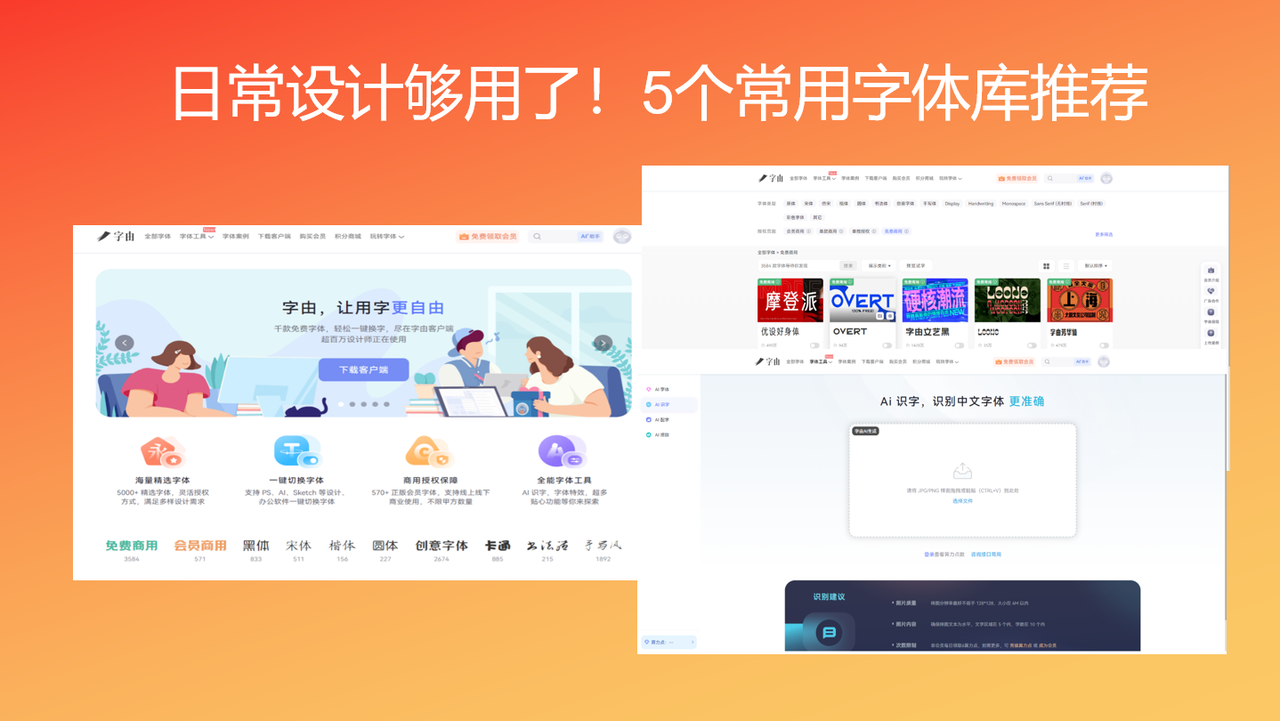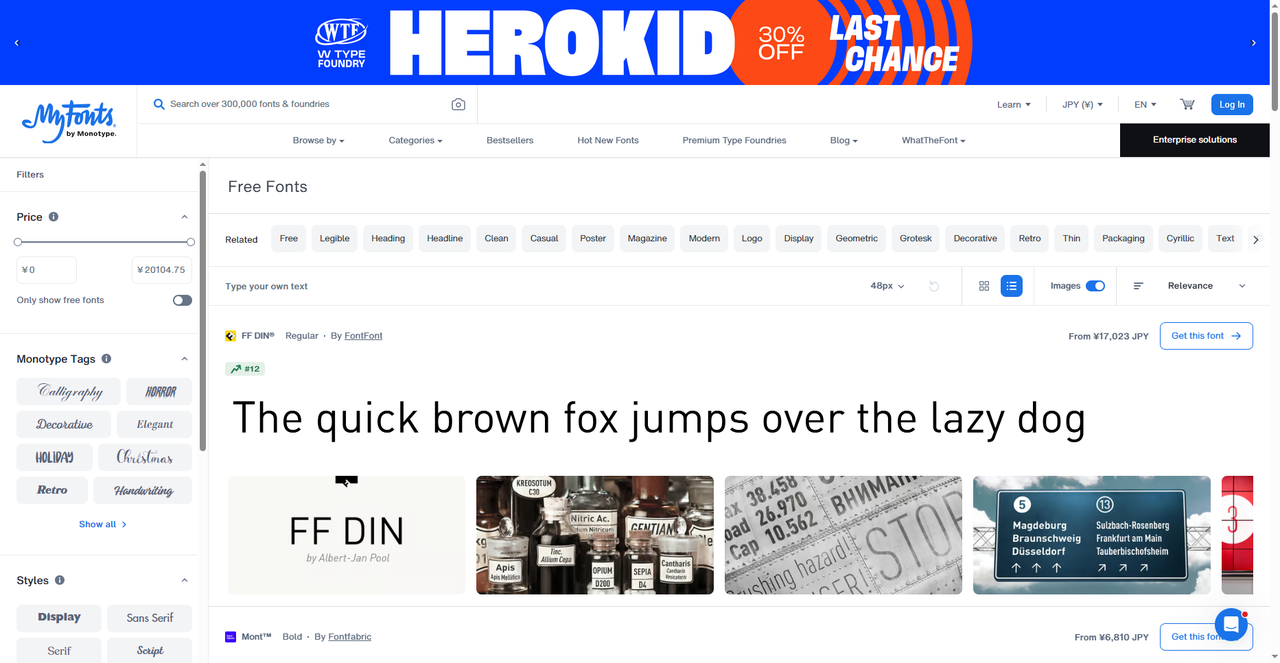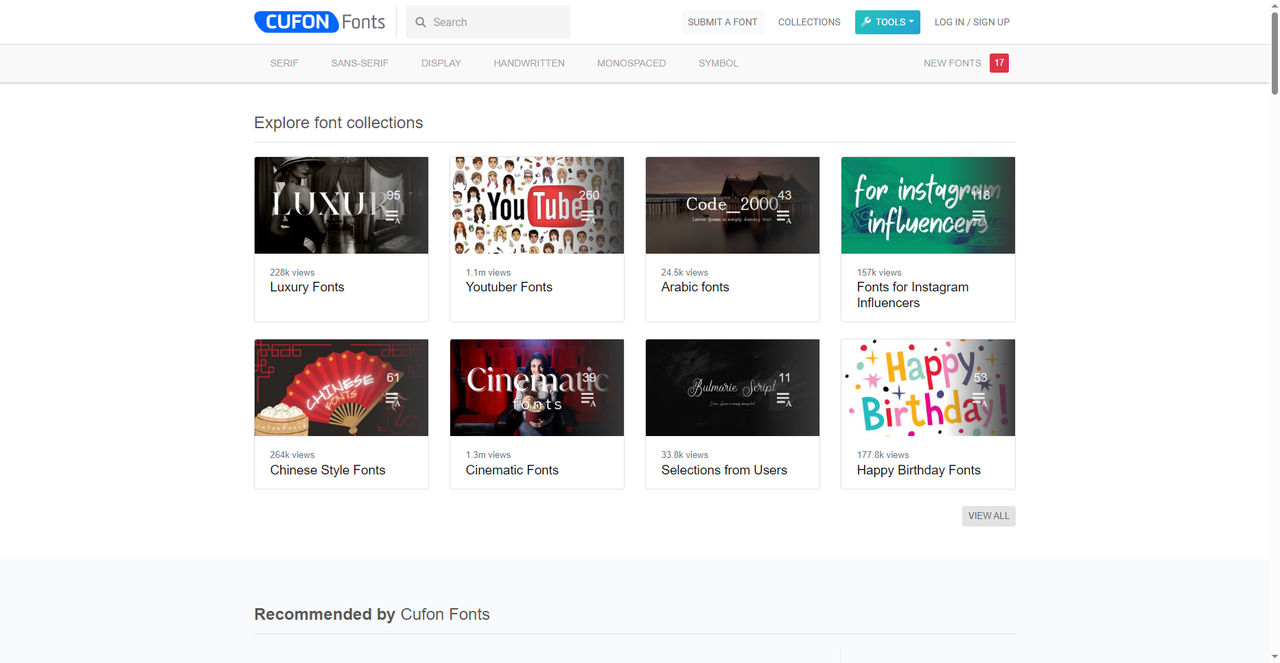
日常设计够用了!5个常用字体库推荐
如果你是刚做设计的新人,肯定免不了会以为好字体是要找的,一开始会到处问别人用什么字体,或者是看一些字体推荐,收藏了很多文章,结果真的要开始做设计项目的时候还是不知道怎么下手。但其实好的字体是要靠积累的,而不是现用现找,这样只会使自己设计思路更乱。那我今天就会给大家分享5 个我用着十分顺手的常用字体库,没有灵感的时候就可以随时点开翻看,遇到好用的就收藏积累起来,这几个都是我打开过无数次、真正能用到日常设计里的字体库网站。
第一个要推荐的常用字体库是字由。字由自从创立以来便一直致力于解决设计师群体的用字困难问题。2017年,字由客户端正式发布,被粉丝们热情地称为“字体应用管理神器”,并且目前字由还开通了客户端,要比网页面的功能更加全面,使用起来会更加便捷。
字由之所以能够成为我的常用字体库的最主要原因是它有着个人云字库管理功能,之前我都是把自己的字体包存在U盘里,但是一旦丢失将是不可挽回的损失。字由则替我完美地解决了这个难题,它支持上传本地字体到云端,只要账号还在,换设备登录依旧可以激活使用,电脑坏了、U盘丢了再也不是令我头疼的事情,只要账号还在,字体就一定在。
其次,字由身为我日常最常用到的字体库还有一个重要原因就是它目前有超过 3000 款可商用的免费字体,完全不用担心版权问题。如果是在网上找的资源,则要面临版权问题和使用限制问题,在字由的话会直接给你按分类归纳好哪些字体是个人使用的,哪些字体又是可以商用/免费商用的,十分便捷!
最主要是的,我们平时在做设计的时候基本上都会用到 PS、 AI、Figma、Sketch、CDR 等软件,之前要是想换字体的话基本上需要重启安装,但是有了字由以后你可以实现一键切换字体。在软件里选中文字图层,回到字由客户端点击想要的字体,文字实时切换,不需要下载、安装、重启。
并且字由还有配套的 AI 智能工具,完全无须担心设计上遇到的相关难题,不论是字体搜索还是字体特效设计,字由都可以帮你搞定。
2、HEROKID
HEROKID 是一个精品字体销售平台,从配图我们可以看到正在展示 FF DIN 这款经典字体。FF DIN 由 Albert-Jan Pool 设计,是工业设计感和现代主义风格的代表字体,广泛应用于品牌、导视系统等领域。在网站的左侧有详细的筛选器,可以按价格、风格(如 Clean、Casual、Geometric、Grotesk、Retro 等)、用途(Heading、Poster、Magazine、Logo、Packaging)来筛选字体。如果你在寻找高品质的商业字体,这里是个不错的起点。虽然大部分需要付费,但字体质量很高,适合对品牌调性有要求的项目。这算是我常用的字体库推荐,毕竟设计并不能全部要依靠免费内容,有时候为优质资源付费也是必要的事情。
3、Cufon Fonts
Cufon Fonts 是一个运营多年的老牌字体网站,分类清晰,首页顶部有 Serif、Sans-Serif、Display、Handwritten、Monospaced、Symbol 等常用分类。这个我常用的字体库主要特色是它的字体专题合集功能,从图中不难看出它在主页就已经为我们整理好了各种字体合集:
- Luxury Fonts(奢华风格字体)
- outuber Fonts(适合视频创作者的字体)
- Arabic Fonts(阿拉伯语字体)
- Fonts for Instagram(适合社交媒体的字体)
- Chinese Style Fonts(中国风字体)
- Cinematic Fonts(电影感字体)
- Happy Birthday Fonts(生日主题字体)
不仅仅是这些,还有更多内容你可以去探索和尝试,并且每个合集保底都有几十款字体,点进去就可以浏览了。另外你还可以参考大家的推荐,很多人气推荐字体也十分不错。
4、FontSpace
FontSpace 在我这里也是老熟人了,它是一个社区驱动的免费字体平台,首页展示的字体都配有详细的风格标签和描述。它和上一个推荐的平台有很多相似之处,之所以说常用还是因为它可以和上一个平台搭配使用,如果上一个没有喜欢的就可以转来这个平台看看,使用逻辑并无差别。在这个网站里每款字体都有详细的设计师信息和风格描述,方便判断是否适合你的项目。FontSpace 的字体质量普遍较高,且大部分免费,是日常设计的可靠来源。
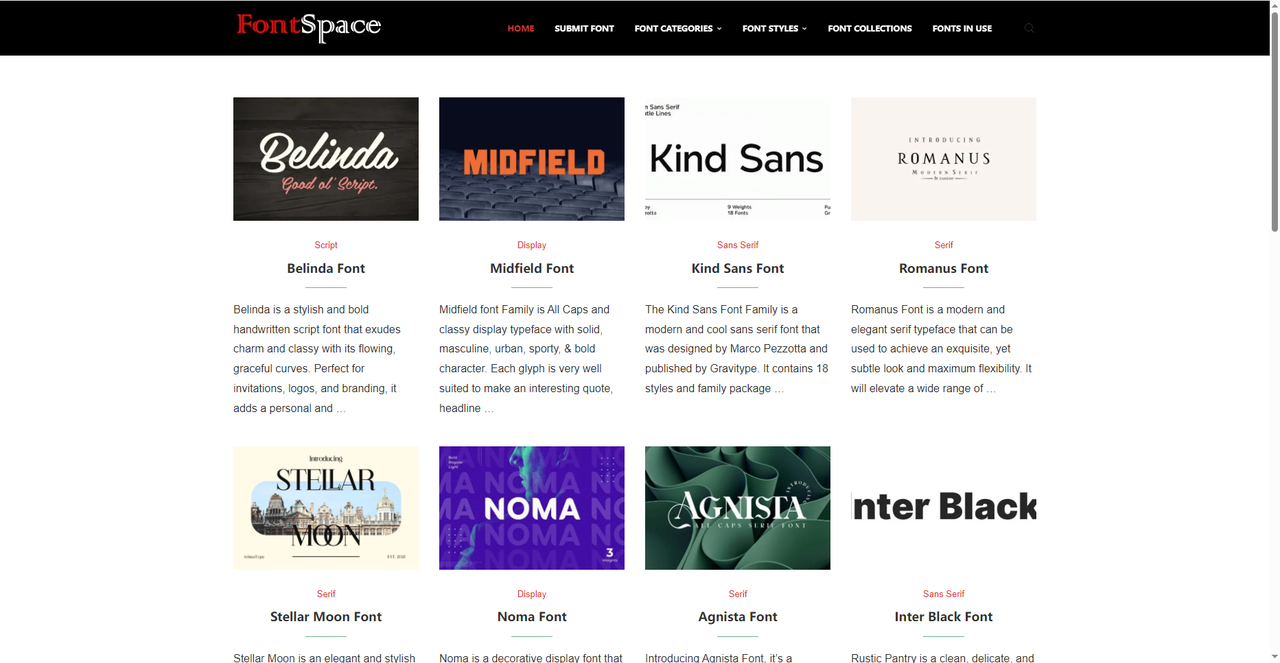
5、FONT2U
接下来要介绍的这款常用字体库可了不得,目前网站收录了 167379 款字体。它的分类极其细致,主页有大量标签,而且网站还提供了详细的字体技术信息,比如是否带重音符号(Accented)、是否支持欧元符号(Euro symbol)、是否包含俄语/希腊语/希伯来语/阿拉伯语/中文/日文/韩文字符等。这对于需要多语言支持的设计项目来说非常实用。
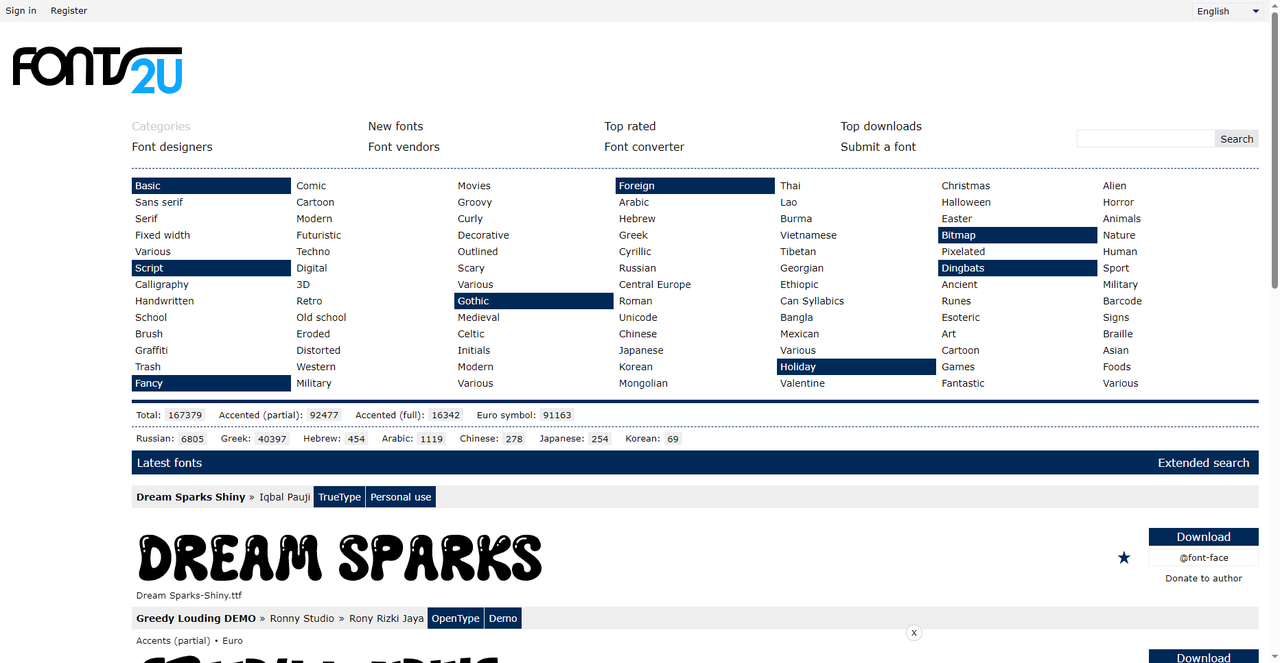
这 5 款常用字体库绝对是我精挑细选,十分推荐的。但是如果要说最近最常用的字体库那无疑是字由,在之前的内容中我也提到过字由可以包揽一切字体相关内容,从实用的功能再到海量字体库,甚至还不用担心版权相关问题,还有个人云字库,随便拿一个出来都能让我设计的体验感直线上升。如果你也在找一个能长期用下去的字体库,不妨从字由开始试试。